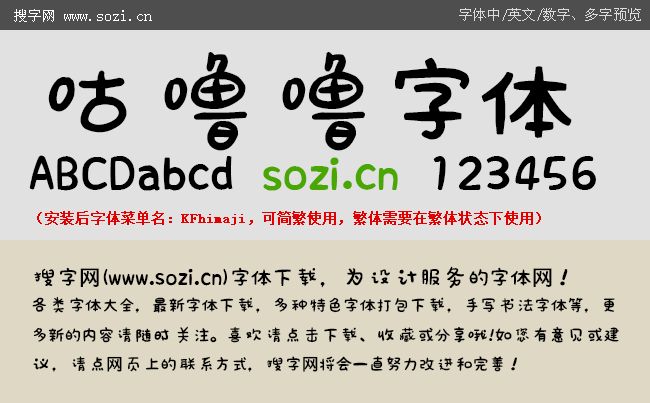
咕嚕嚕字體
搜字網(wǎng)給大家提供一款很有趣的手機(jī)中文字體下載。修改者給他起了很萌的名字咕嚕嚕字體,光看名字就很萌了有木有,這款手機(jī)字體是模仿兒童手寫(xiě)的POP字體。趣味性實(shí)足,該手機(jī)字體個(gè)性實(shí)足,趣味性強(qiáng),又保持了文字的識(shí)別度,特別適合喜歡手機(jī)字體個(gè)性一些的朋友在手機(jī)上安裝使用。